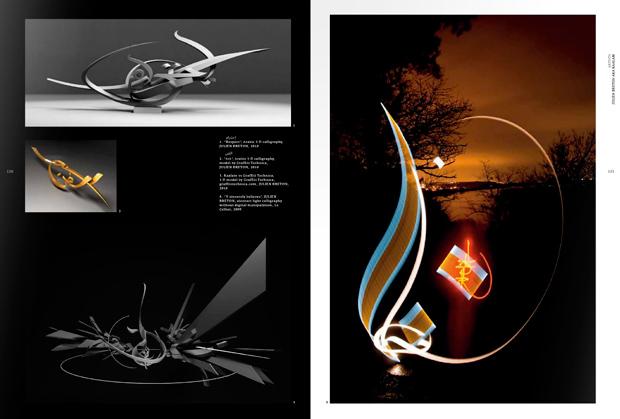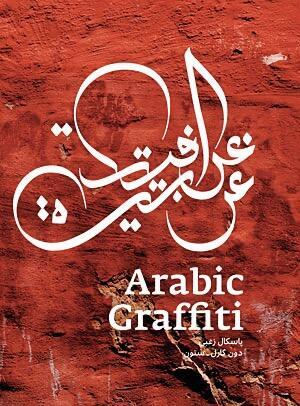
Nach Calligraffiti kommt aus dem Verlag From Here to Fame ein weiteres Werk zur typografischen Straßenkultur. Schwerpunkt ist diesmal der mittlere Osten und der Einfluss der urbanen Schriftkultur der arabischen Welt. Geschrieben und zusammengestellt wurde das Buch vom libanesischen Typografen Pascal Zoghbi und dem Graffiti-Künstler Stone aka Don Karl.
Neben den zahlreichen Fotos enthält das Buch auch Essays, die sich mit den grafischen Traditionen und ihrer heutigen Anwendung sowie den sozialen und kulturellen Hintergründen der Graffiti-Kunst in der arabischen Welt auseinandersetzen.